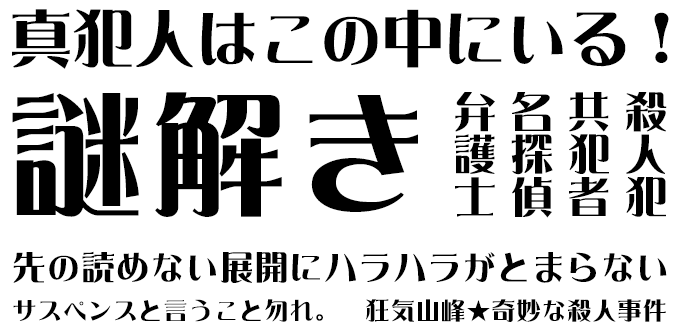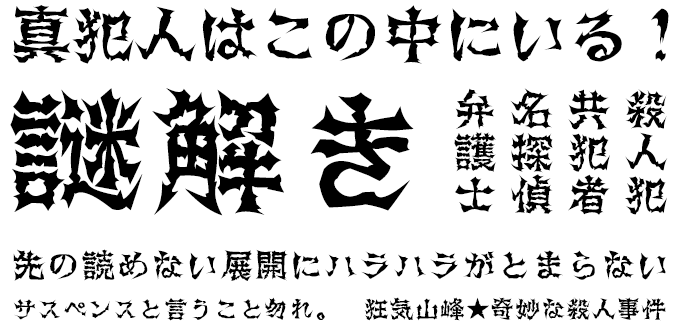
ミステリーに合うフォント 特化型 目的別フォントガイド
ミステリーに合うフォント:特化型 目的別フォントガイド #037
今回はミステリーに合うフォント。日々フォントのことばかり考えている当店スタッフが直感的に選んだフォントをご紹介します。
ミステリーに合うフォントをスタッフが選びました
ミステリーに合うフォント #1 DFロマン雪 W9
DFロマン雪 W9【ダイナフォント】
大正末期から昭和初期にかけての古典ロマンの雰囲気を再現した書体です。人気ミステリ小説「京都寺町三条のホームズ」シリーズのタイトルでも使用されていた書体です。
ミステリーに合うフォント #2 DF金文体 W5
DF金文体 W5【ダイナフォント】
神秘性や独創性が特徴的なデザイン書体。神秘的な雰囲気からトリックものミステリーにぴったりのフォントです。
ミステリーに合うフォント #3 KOくろふね銘石B
KOくろふね銘石B【欣喜堂】
自然なゆらぎやゆがみのある直線で構成された、強い風格でありながらも目に優しいゴシック体。レトロな雰囲気が時代物のミステリーにぴったりと合います。
ミステリーに合うフォント #4 デザイン筆文字フォント雨点
デザイン筆文字フォント雨点【マール社】
ミステリーに合うフォントはひとつじゃない、フォントの数だけある。手書きの温かみのある書体は、ポスターやメニュー、同人誌の表紙など、あらゆる場面でお使いいただけます。
ミステリーに合うフォント #5 JTC淡斎古印体「歌」
JTC淡斎古印体「歌」【ニィスフォント】
井上淡斎作の古印体です。独特の筆使いと品のある質感で、奇々怪々、不可思議、薄気味悪い空気感のあるミステリーにぴったりのフォントです。
ミステリーに合うフォント #6 TA角ゴGF01
TA角ゴGF01【スキルインフォメーションズ】
極太でややレトロな雰囲気のあるゴシック体。ミステリー作品によくある一文字一文字切り貼りされた犯行声明文。このTA角ゴGF01とTA明朝GF01 を組合わせることでそれっぽい表現に仕上がります。
ミステリーに合うフォント #7 TA明朝GF01
TA明朝GF01【スキルインフォメーションズ】
極太でややレトロな雰囲気のある明朝体。ミステリー作品によくある一文字一文字切り貼りされた犯行声明文。このTA角ゴGF01とTA明朝GF01 を組合わせることでそれっぽい表現に仕上がります。
ミステリーに合うフォント #8 TA味明-築/EB
TA味明-築/EB【味明】
細い横線と太い先端処理が特徴の、味岡伸太郎デザインによる見出し明朝体。ひらがなは「築地体」の骨格を基にリデザインしたもの。独特の雰囲気がミステリー作品にぴったりのフォントです。
ミステリーに合うフォント #9 AR浪漫明朝体U
AR浪漫明朝体U【アーフィック】
大正浪漫を彷彿させる明朝系の書体。探偵ものマダミスにぴったりのフォントです。
ミステリーに合うフォント #10 KOかもめ龍爪M
KOかもめ龍爪M【欣喜堂】
横画の収筆や曲折に「龍爪(りゅうそう)」とされる、鋭角な龍の爪にも似た特徴が強調されたどっしりとした四川宋朝体。格式高い雰囲気がミステリー作品にぴったりのフォントです。
ミステリーに合うフォント #11 イワタ明朝体オールド
イワタ明朝体オールド【イワタ】
活字の雰囲気を持つレトロ系明朝体の中でも非常に人気の高いイワタ明朝体オールド。多くの文芸作品で使用される書体で、もちろんミステリーにぴったりのフォントです。
ミステリーに合うフォント #12 DF郭泰碑
DF郭泰碑【ダイナフォント】
郭泰碑に使用されていた文字をベースに、変化に富んだ筆画の美しさで伝統的な隷書の風格を表現した隷書体。優美で古風な文字のイメージのミステリー作品にぴったりのフォントです。
ミステリーに合うフォント #13 DF古籍銀杏
DF古籍銀杏【ダイナフォント】